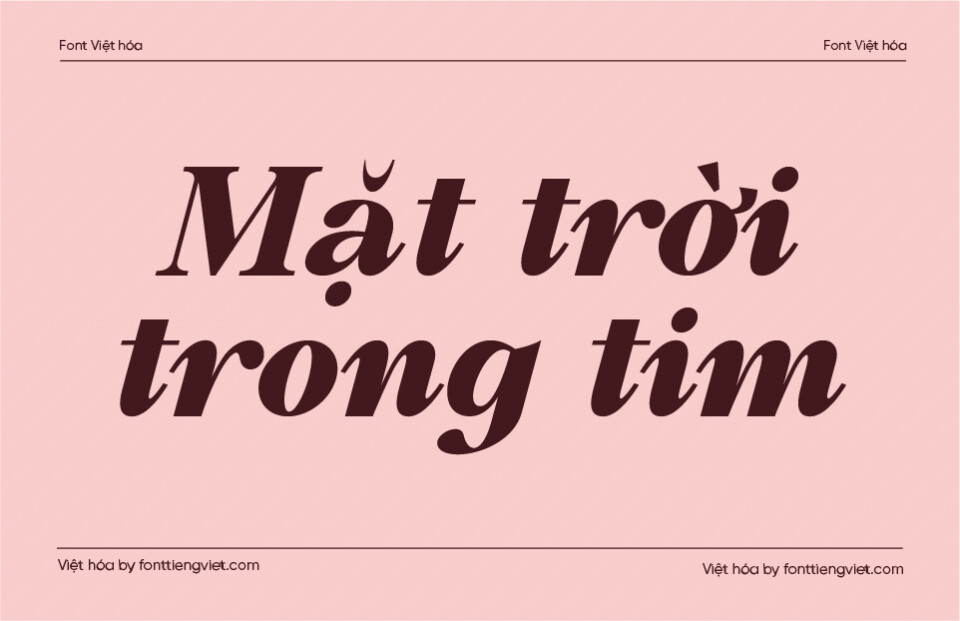
Tải Bộ Font Việt hóa 1FTV VIP Shiny Black Sang Trọng Cho Thiết KếTrong thế giới thiết kế đồ họa hiện đại, việc lựa chọn một bộ Font Miễn Phí chất lượng luôn là ưu tiên hàng đầu của các bạn học sinh và sinh viên. Đặc biệt, mẫu Font Việt hóa 1FTV VIP Shiny Black đang trở thành tâm điểm chú ý nhờ phong cách mạnh mẽ, bóng bẩy và vô cùng chuyên nghiệp. Đây là một bộ font chữ thuộc phân khúc cao cấp nhưng đã được chỉnh sửa để phù hợp hoàn toàn với bảng mã tiếng Việt, giúp người dùng dễ dàng sáng tạo các nội dung học tập hay dự án cá nhân mà không lo lỗi font hay thiếu dấu. Với đường nét dày dặn và hiệu ứng thị giác ấn tượng, bộ chữ này mang lại cảm giác hiện đại và đầy năng lượng cho mọi khung hình.Khám phá sức hút của Font Việt hóa 1FTV VIP Shiny BlackBộ Font Việt hóa 1FTV VIP Shiny Black sở hữu những đặc điểm nhận dạng riêng biệt, khó có thể nhầm lẫn với các phông chữ phổ thông khác trên thị trường. Điểm nhấn lớn nhất nằm ở độ dày của các nét chữ (Black weight), kết hợp cùng các góc bo tròn tinh tế tạo nên sự hài hòa giữa vẻ cứng cáp và nét mềm mại. Điều này rất phù hợp khi các em học sinh muốn thiết kế bìa báo tường, làm slide thuyết trình hay trang trí thời khóa biểu cá nhân thêm phần sinh động.Ưu điểm khi sử dụng Font Việt hóa 1FTV VIP Shiny Black trong học tậpLý do khiến nhiều người lựa chọn Font Việt hóa 1FTV VIP Shiny Black chính là khả năng hiển thị rõ nét trên cả màn hình máy tính lẫn bản in. Các ký tự tiếng Việt như á, ế, ừ, hỗ được chăm chút tỉ mỉ, đảm bảo độ cân đối về khoảng cách và hình dáng. Đối với các bạn yêu thích làm video hay sáng tạo nội dung trên mạng xã hội, bộ font này giúp tiêu đề video trở nên nổi bật và thu hút người xem ngay từ cái nhìn đầu tiên. Ngoài ra, tính ứng dụng cao của nó còn cho phép kết hợp linh hoạt với nhiều tông màu khác nhau, từ màu pastel nhẹ nhàng đến các màu neon rực rỡ.Cách ứng dụng Font Việt hóa 1FTV VIP Shiny Black hiệu quả nhấtĐể tận dụng tối đa vẻ đẹp của Font Việt hóa 1FTV VIP Shiny Black, bạn nên sử dụng nó cho các tiêu đề chính hoặc các đoạn văn bản ngắn cần sự chú ý. Tránh sử dụng bộ font này cho các đoạn văn bản dài vì độ dày lớn có thể gây mỏi mắt cho người đọc. Thay vào đó, hãy phối hợp nó với một font chữ không chân (Sans-serif) mảnh hơn để tạo ra sự tương phản chuyên nghiệp. Trong các bài thuyết trình ở trường, việc dùng font chữ này cho các từ khóa quan trọng sẽ giúp thầy cô và bạn bè dễ dàng ghi nhớ nội dung bài giảng hơn.Lưu ý khi cài đặt và sử dụng font chữ việt hóaViệc cài đặt bộ Font Việt hóa 1FTV VIP Shiny Black rất đơn giản, bạn chỉ cần tải tệp tin về, giải nén và nhấn chuột phải chọn Install. Tuy nhiên, hãy luôn kiểm tra bản quyền nếu bạn có ý định sử dụng cho các mục đích thương mại lớn. Đối với mục đích học tập và chia sẻ trong cộng đồng nhà trường, đây thực sự là một món quà tuyệt vời giúp nâng tầm thẩm mỹ cho mọi tác phẩm sáng tạo của thế hệ trẻ Việt Nam hiện nay.Kết luận về bộ phông chữ 1FTV VIP Shiny BlackTổng kết lại, Font Việt hóa 1FTV VIP Shiny Black không chỉ là một công cụ thiết kế mà còn là nguồn cảm hứng sáng tạo vô tận cho các bạn học sinh. Việc sở hữu một bộ font chữ đẹp và chuẩn tiếng Việt sẽ giúp bạn tự tin hơn trong các hoạt động ngoại khóa cũng như dự án cá nhân. Hãy ghé thăm trang web Font Miễn Phí, Font Việt Hóa, Font Việt hóa 1FTV VIP Shiny Black thường xuyên để cập nhật thêm nhiều mẫu chữ độc đáo khác. Hy vọng bài viết này đã mang đến cho bạn những thông tin hữu ích để làm mới kho tàng tài liệu thiết kế của mình ngay hôm nay.
Font Việt hóa 1FTV VIP Shiny Black